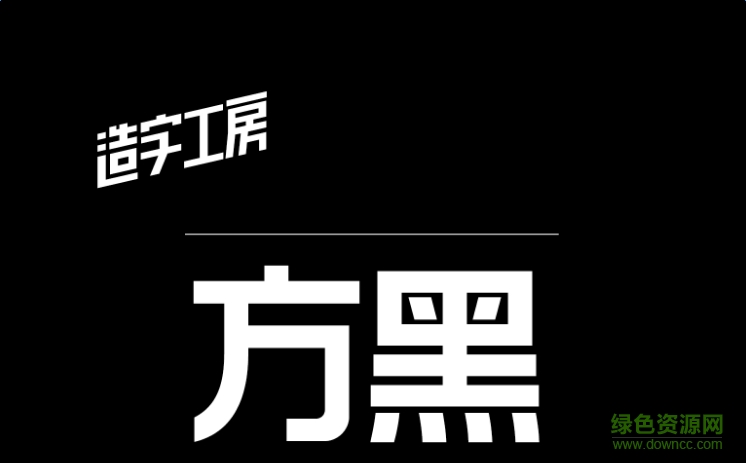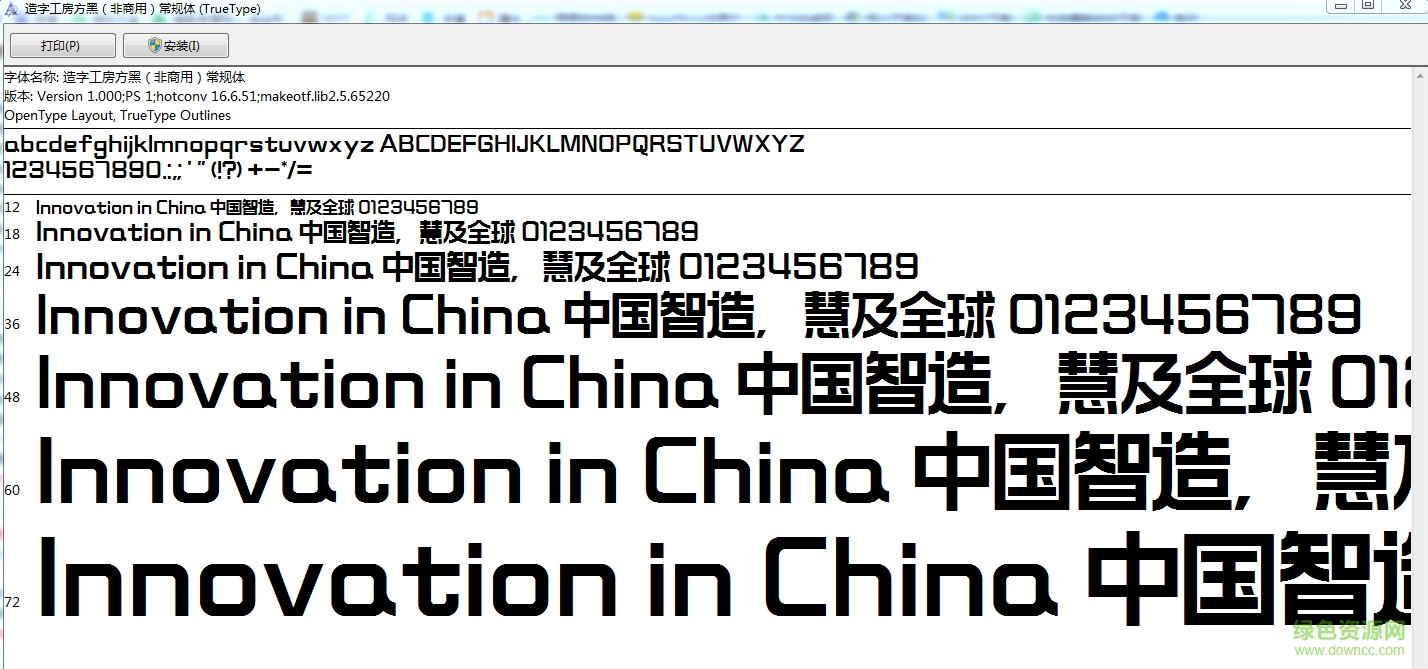
造字工房方黑字體
字體介紹
造字工房方黑體在常見的黑體字形風(fēng)格之上更加平穩(wěn)著力,個性鮮明,筆畫簡潔、大方,引人注目。字形結(jié)構(gòu)嚴(yán)謹(jǐn),實用性強,橫豎筆畫基本保持一致,凸顯出精簡精干的特點。適用于標(biāo)題、廣告或副標(biāo)題用字。
造字工房方黑體